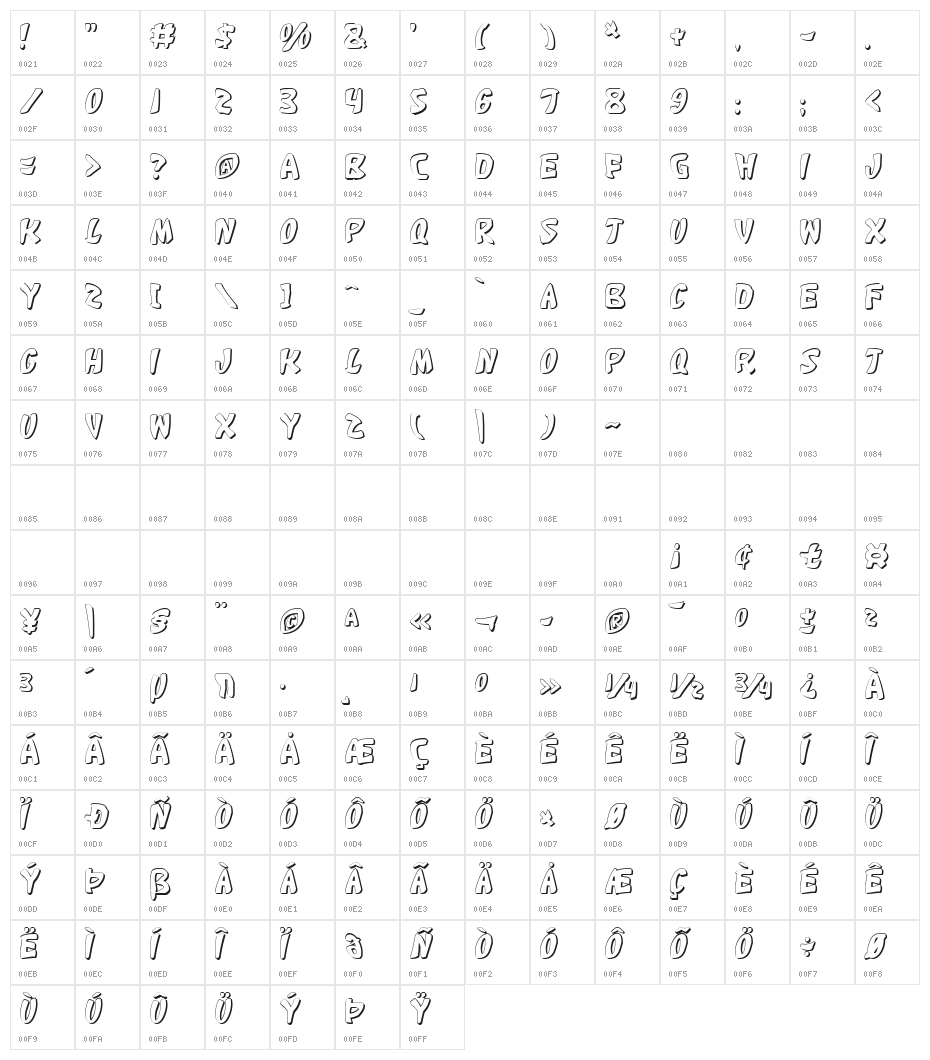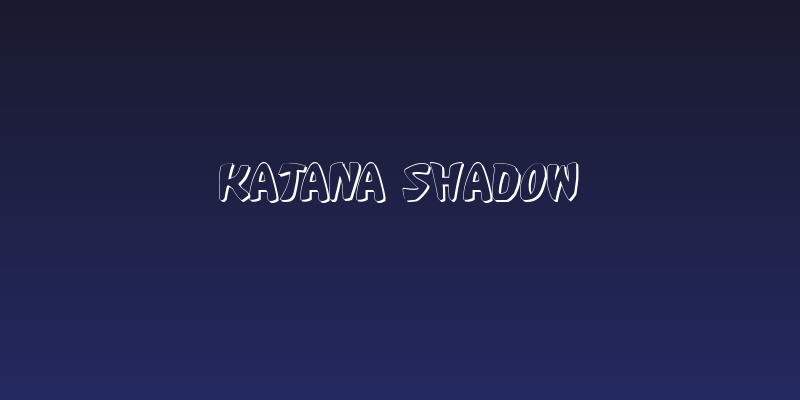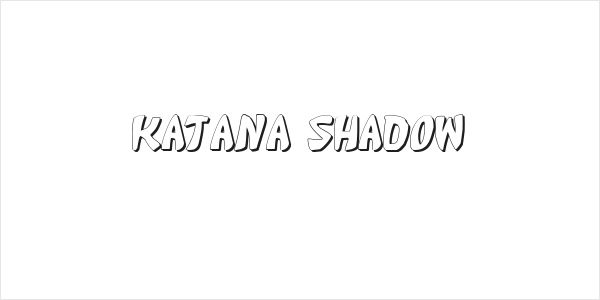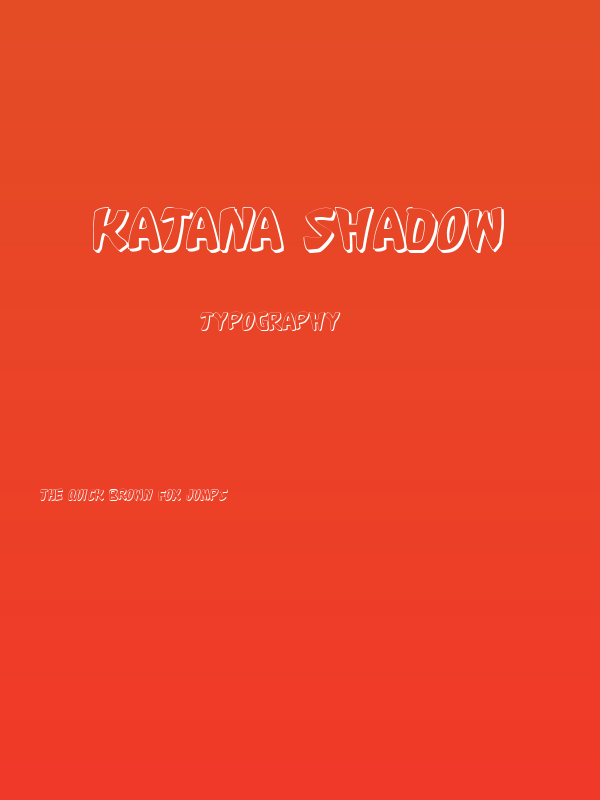
Katana Shadow Font
KATANA-SHADOW 大文字
KATANA-SHADOW 小文字
KATANA-SHADOW その他の文字
| 名前 | Katana Shadow |
| ウェイト | Shadow |
| 全体的なスタイル | Playful, Energetic |
| 用途 | Headlines, Posters, Logos |
| おすすめプロジェクト | Ideal for children's book covers, playful posters, comic strips, and any design needing a fun, energetic typeface. |